5月20号这个日子,现在逐渐被情侣们赋予了“我爱你”的这个意思。在这个年轻化、精神化的节日里,人们通过社交软件或者面对面大胆说爱,那么小编就通过下面几张 字体图片给大家推荐几款充满“爱”的字体吧~
笔芯拼音体:这是一款拼音体,笔画简单,结构放松,圆弧的线条让字体显得更加可爱这款字体的精妙之处在于把点、捺部分的线条改为小爱心,让字里行间充满了爱。不仅适合表白,用于logo设计、广告、动漫都非常合适。
有个恋爱想和你谈:名副其实的告白体,粗细有度的字形上衔接着爱心元素,收笔处线条没有选择尖锐而是圆弧,清新活力的青春气息洋溢而出,用作文艺类书刊、品牌广告和包装设计以及社交网络个性化用字都相当合适。
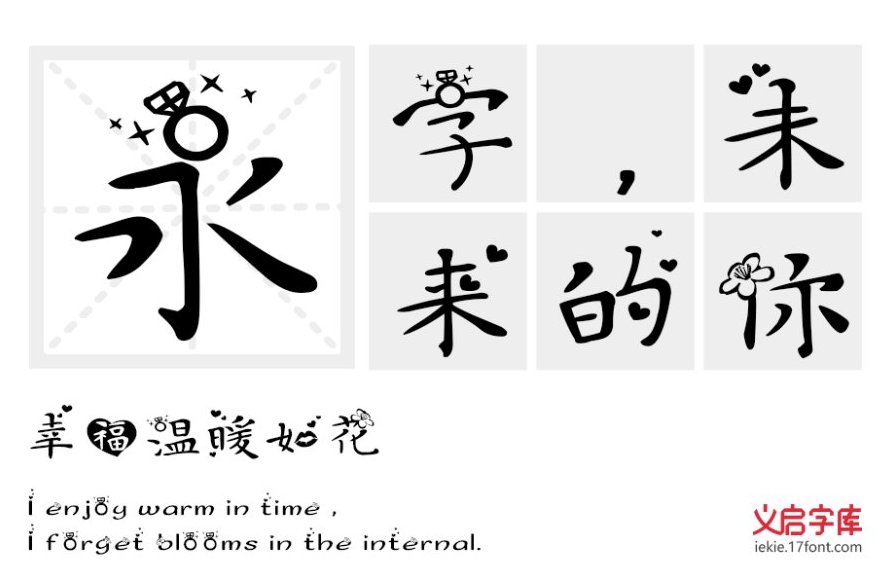
义启心花怒放:这款字体简直就是一款表白、求婚神器。看着这张图片爱多到要溢出来了似的。字形还是保留了清晰感、易于 识别字体,在点、撇上下功夫创作设计戒指、花朵、爱心元素使人心动不已,还适用于婚庆、活动标题、文艺书刊、社交网络个性化用字等领域。